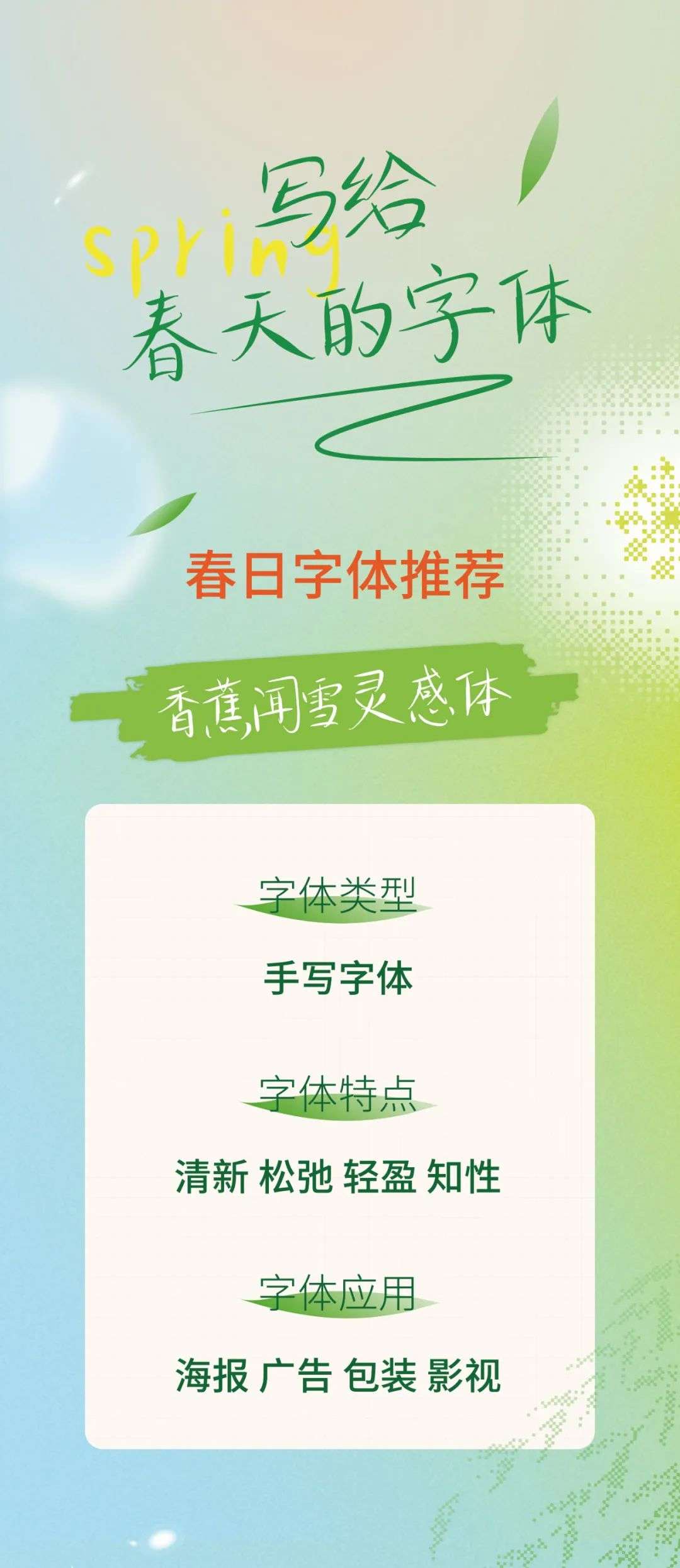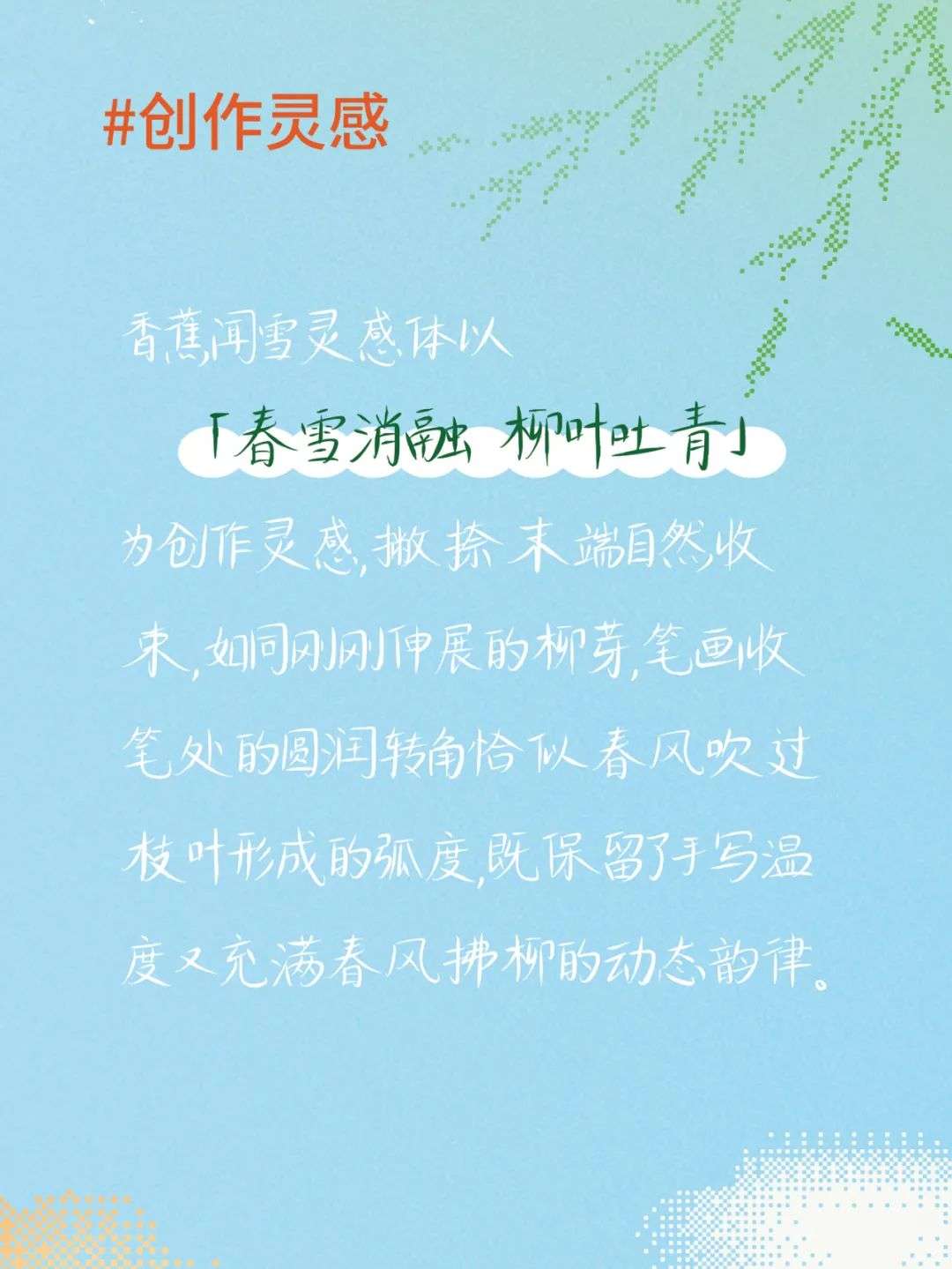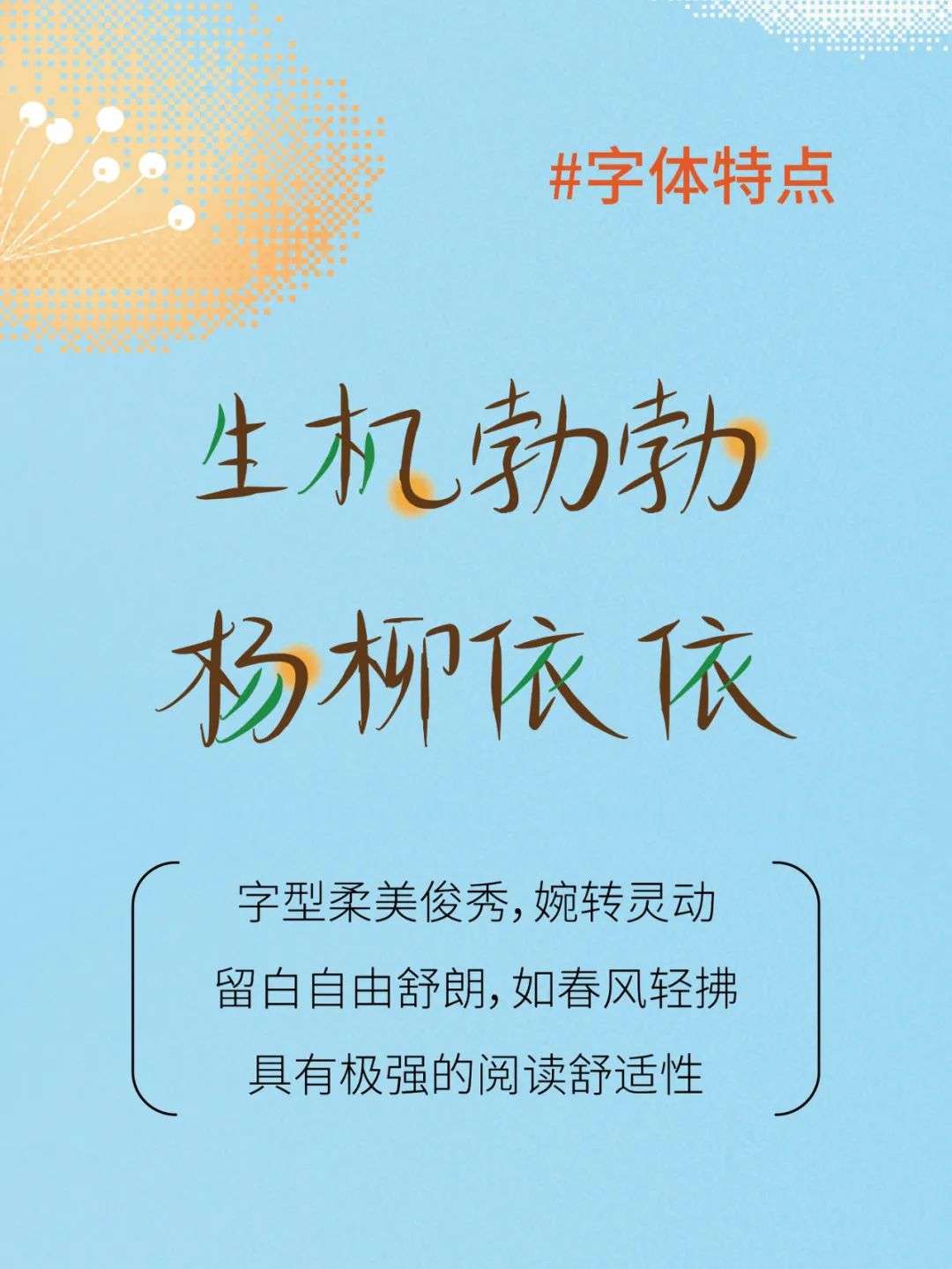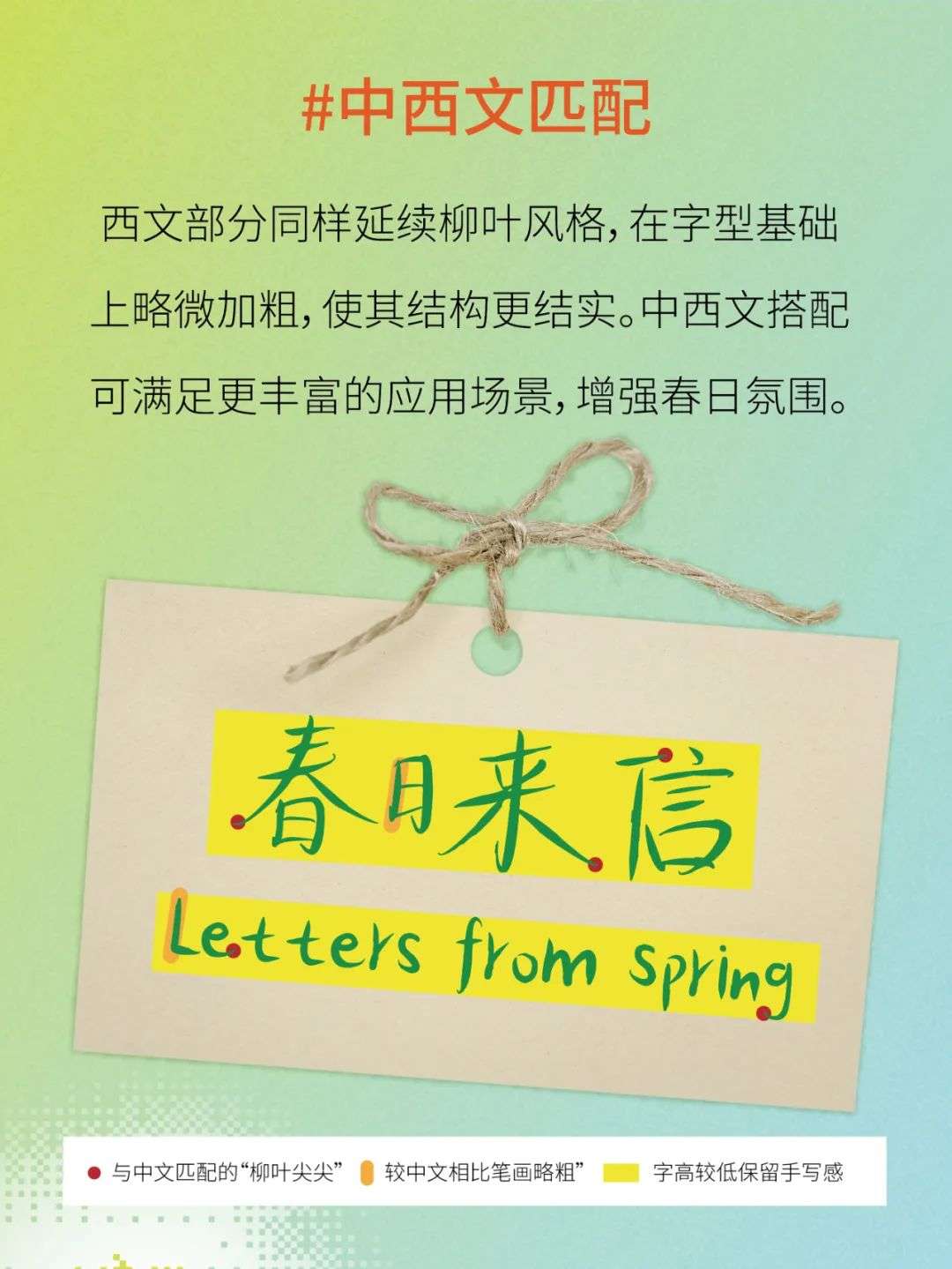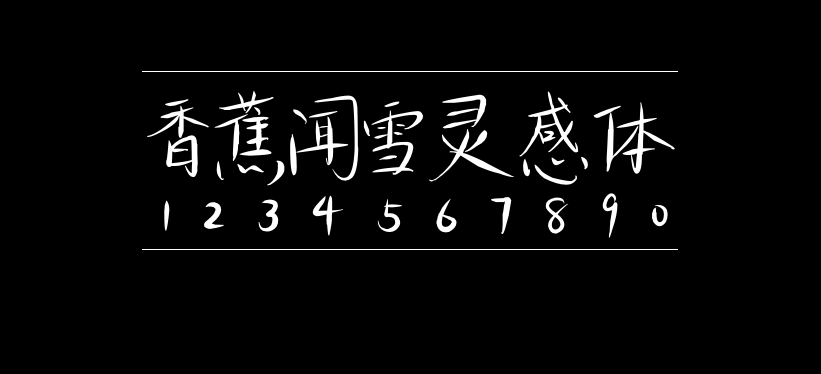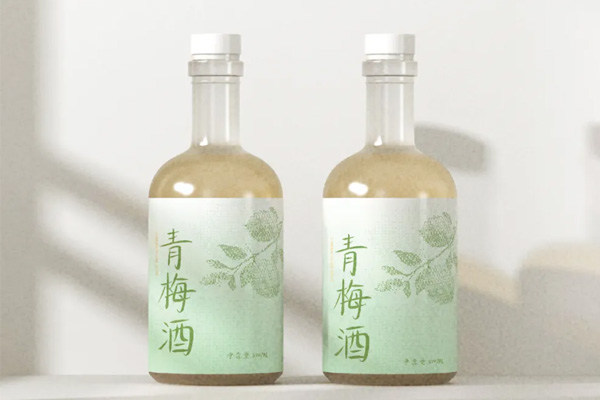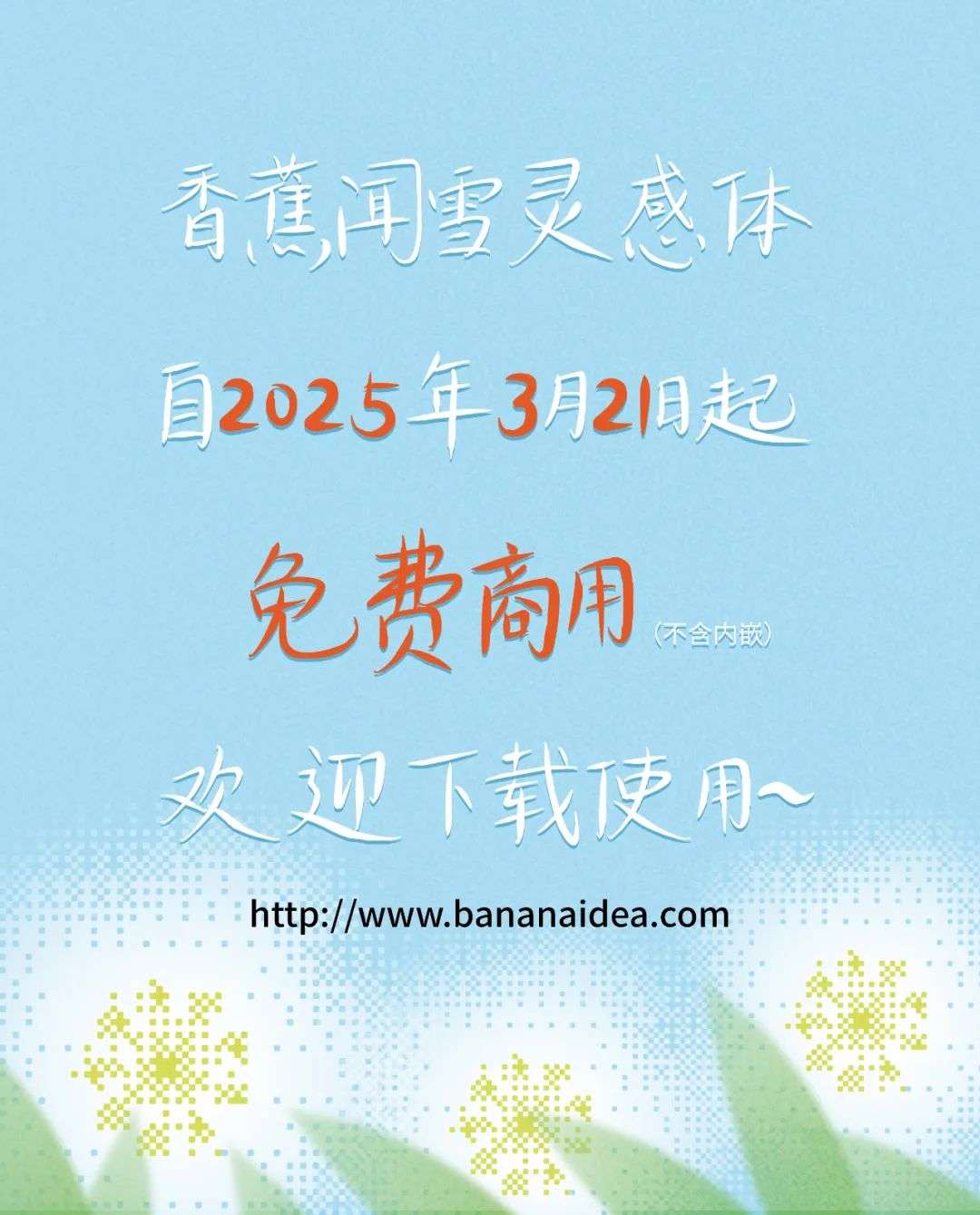
香蕉闻雪灵感体
香蕉闻雪灵感体是香蕉灵感旗下推出的一款免费商用字体,该字体字形俊秀、婉转灵动,透出知性之气。笔画柔美俊秀、刚柔并济,自然洒脱中透露出对冬日第一场雪的期望。
本字体为简体字库,采用OpenType格式,基于中华人民共和国GB2312-80字符集标准,另按需添加101个汉字。共收容字数6864汉字,常用符号100个,共计字符6964个。